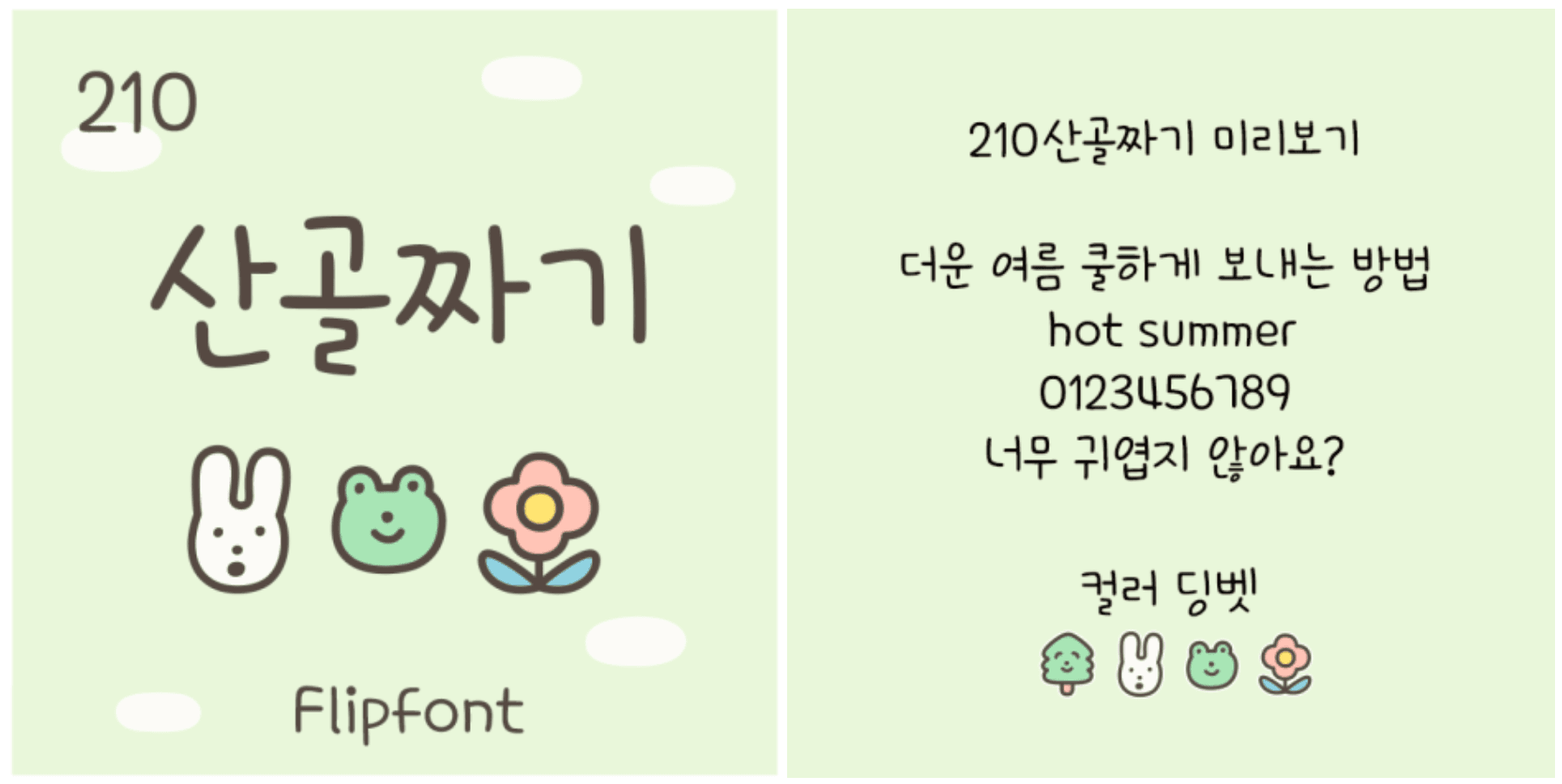
'210산골짜기 Flipfont'는 리듬감과 경쾌함을 표현한 손글씨 느낌의 폰트입니다.
직선을 중심으로 디자인되어 정돈된 인상을 주며, 자소를 크게 구성해 시원시원한 느낌을 강조했습니다.
또한, 자소마다 높낮이를 달리해 자유롭고 유쾌한 분위기를 더했습니다.
* 컬러 딩벳이 추가되어 더욱 풍성한 표현이 가능합니다.
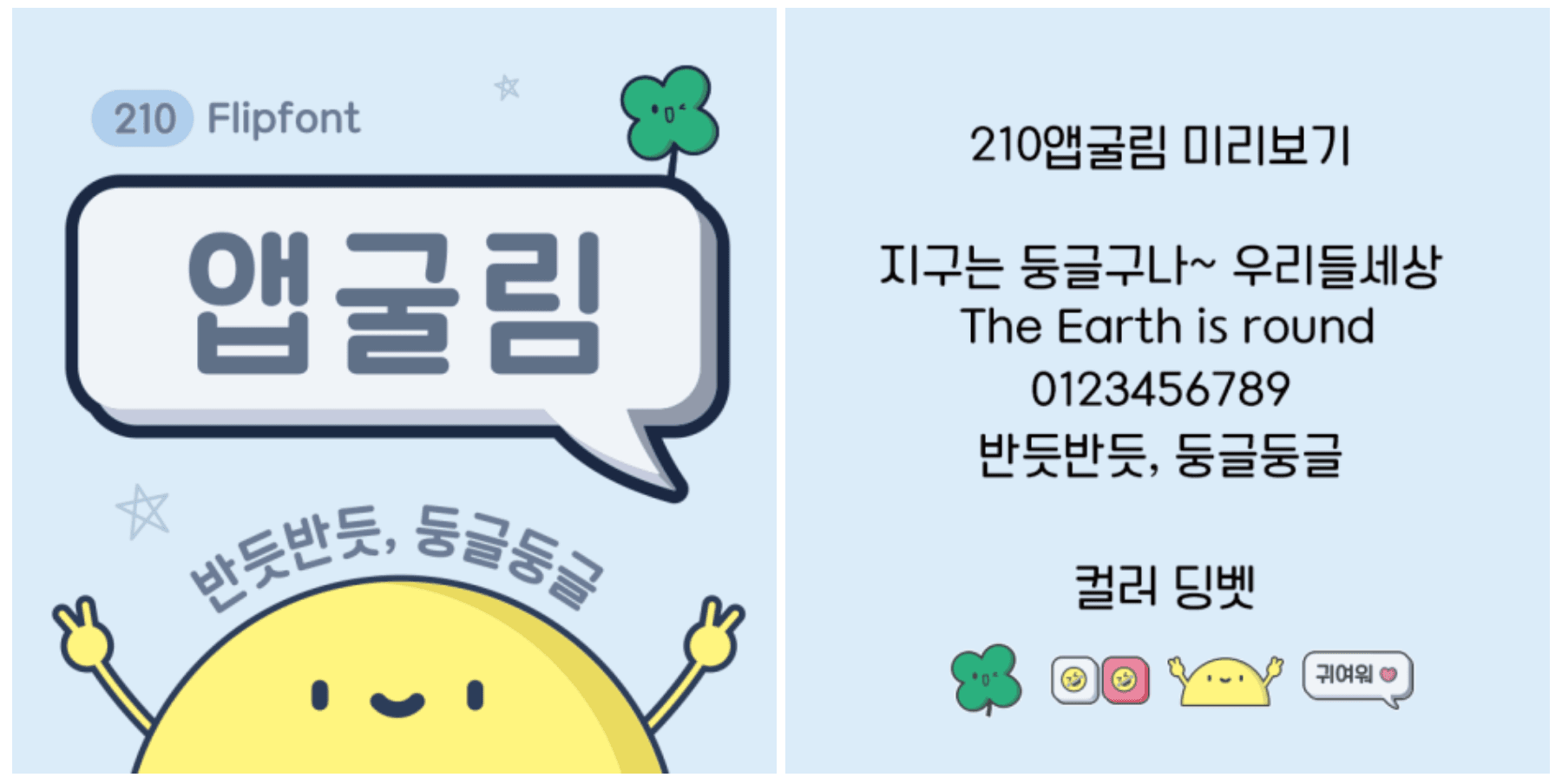
'210앱굴림 Flipfont'는 꽉찬 느낌을 표현한 정감 어리고 귀여운 느낌의 폰트입니다.
글자 크기를 크고 두껍게 디자인해 단단하고 안정감 있는 인상을 주며, 둥글고 부드러운 곡선 처리로 정감 있고 귀여운 분위기를 살렸습니다.
* 컬러 딩벳이 추가되어 더욱 풍성한 표현이 가능합니다.